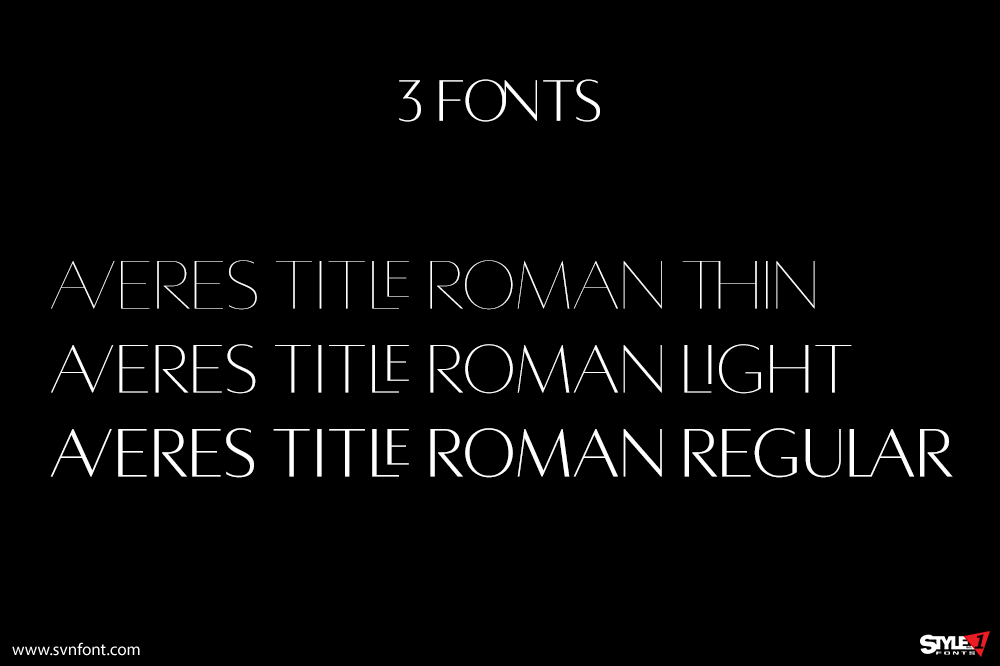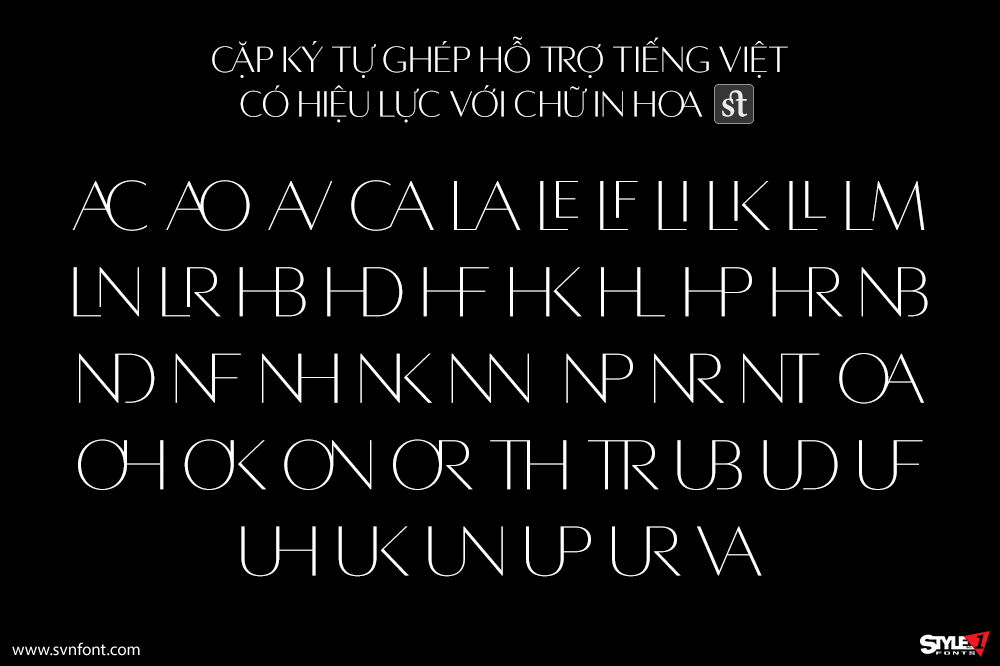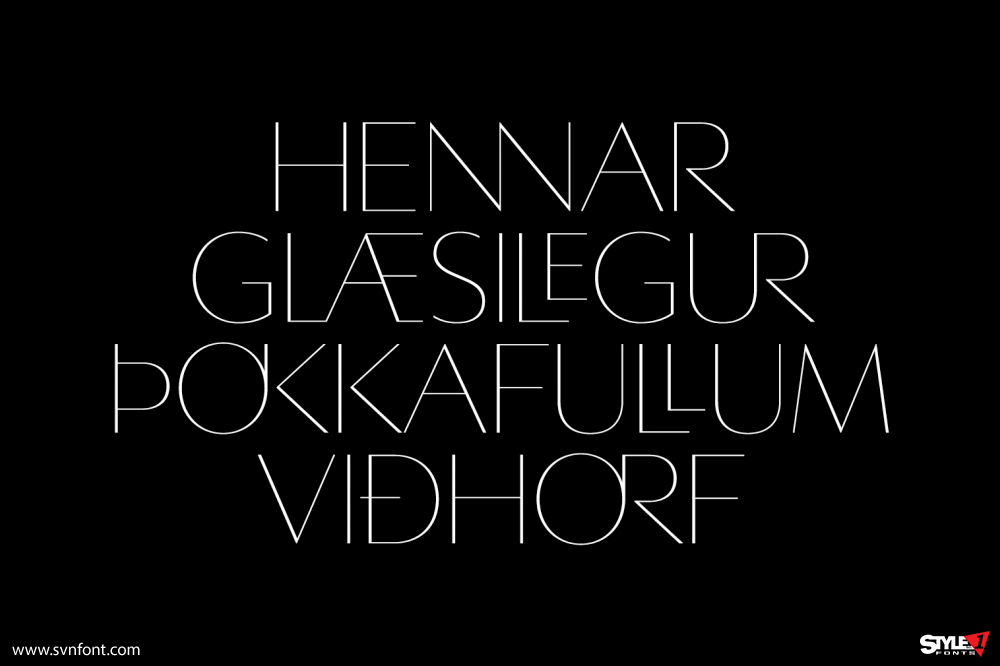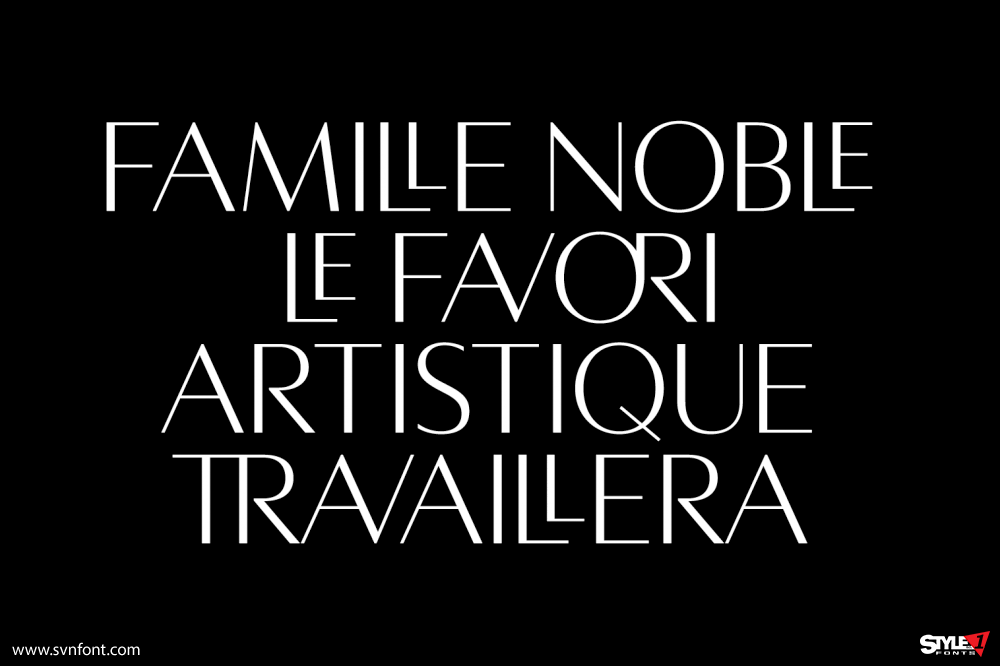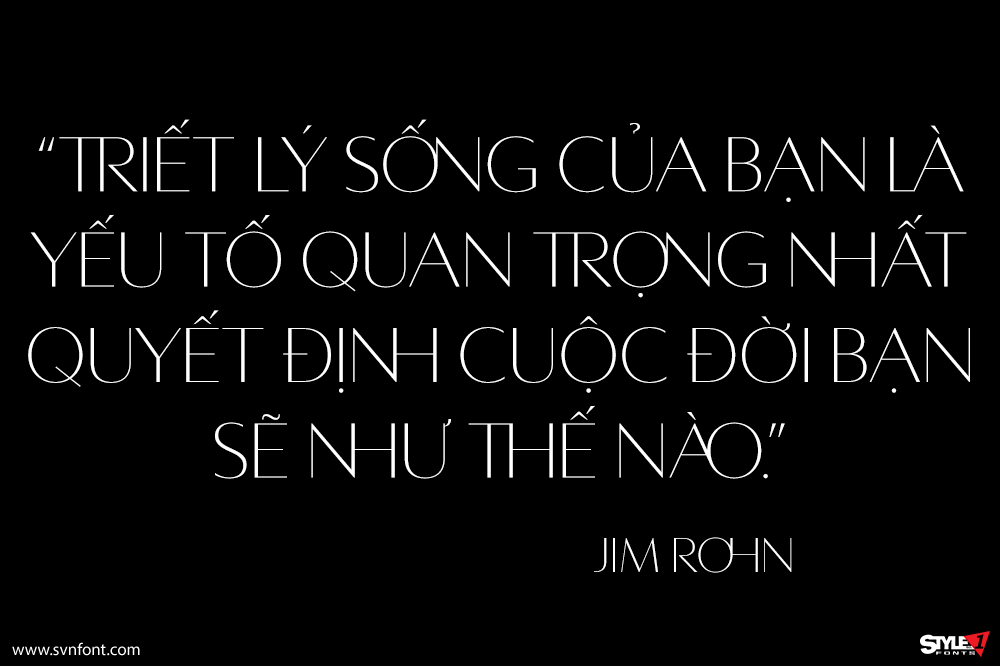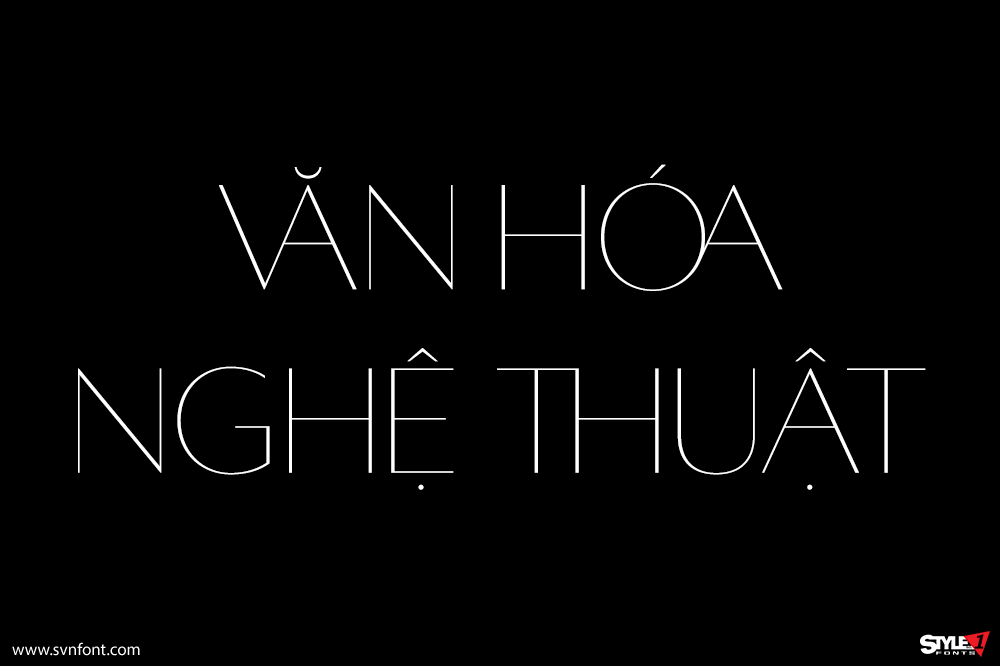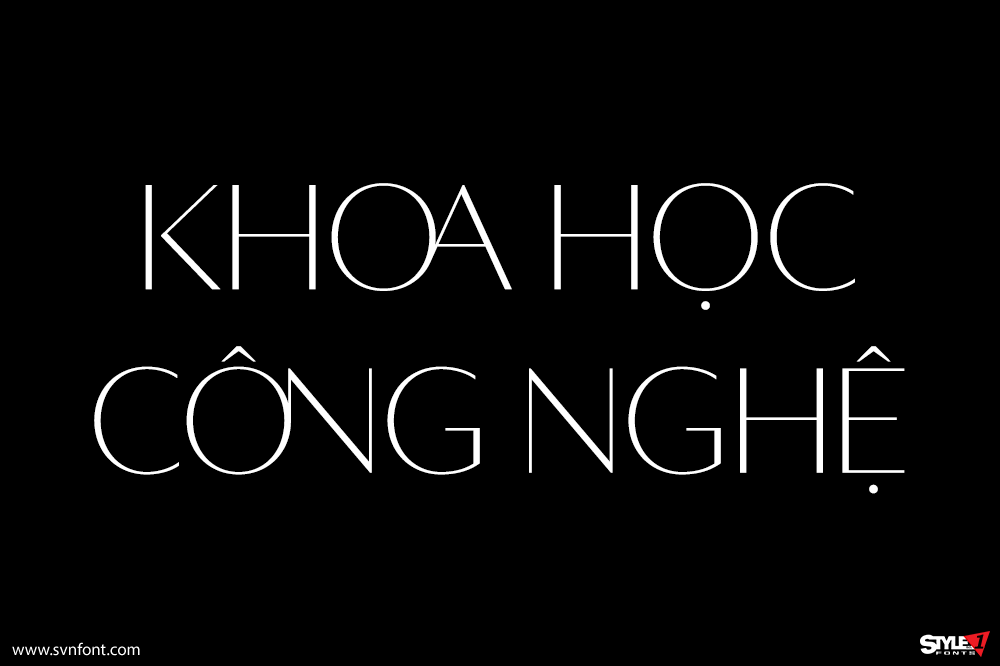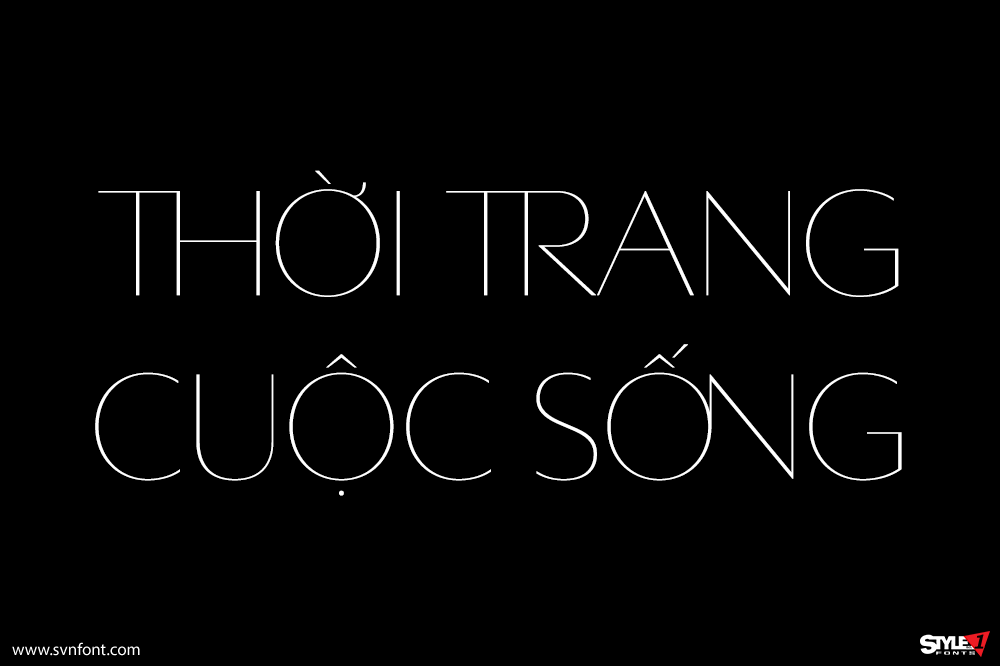
Averes Title Roman là một kiểu chữ sans titling (dành cho tiêu đề) có độ tương phản cao, có sẵn với ba độ đậm. Nó nổi bật với một loạt các bộ chữ nối tùy chọn theo phong cách (stylistic discretionary ligatures) cùng với các biến thể có dấu tương ứng, hỗ trợ nhiều ngôn ngữ.
Nhà thiết kế: Michael Jarboe
*Tính năng ký tự ghép (ligatures) chỉ có hiệu lực đối với chữ hoa (Uppercase)